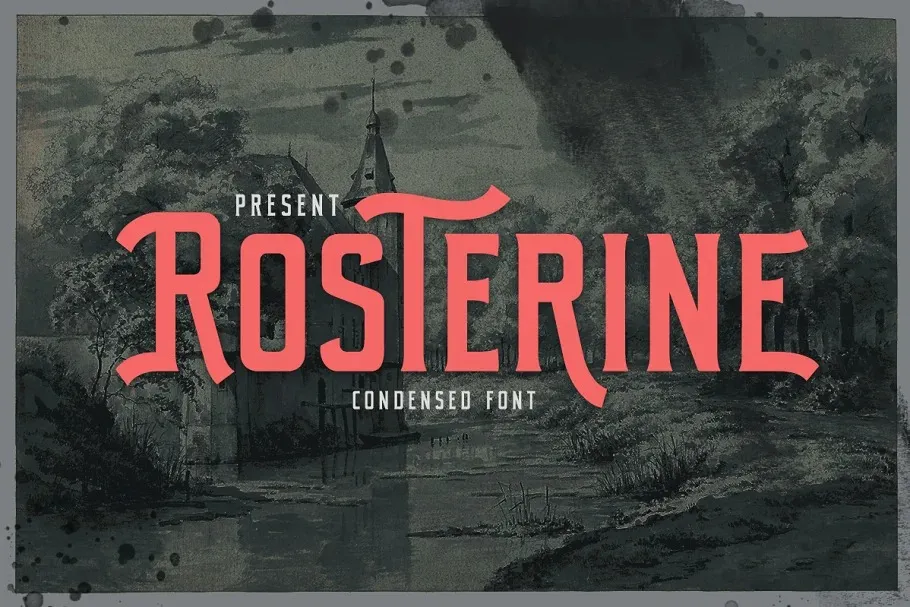
A Rosterine Font é uma tipografia display que traz à tona a essência do estilo vintage com uma pitada nostálgica. Conhecida por sua singularidade em cada caractere, especialmente nas letras maiúsculas, ela se destaca como uma fonte de exibição condensada criada pelo Letterhend Studio. A Rosterine é um tipo gráfico que se destaca não apenas pela sua aparência única e a força das suas características, mas também por seu perfeito aplicação em diferentes formatos formais, como cartões de convite, etiquetas, magazines, livros, cartas de cumprimentos ou casamentos, embalagens, moda, maquiagem, material de escritório, novelos, tags ou qualquer tipo de propósito de propaganda. Esta fonte é perfeita para aqueles que buscam um toque vintage em seus projetos digitais.